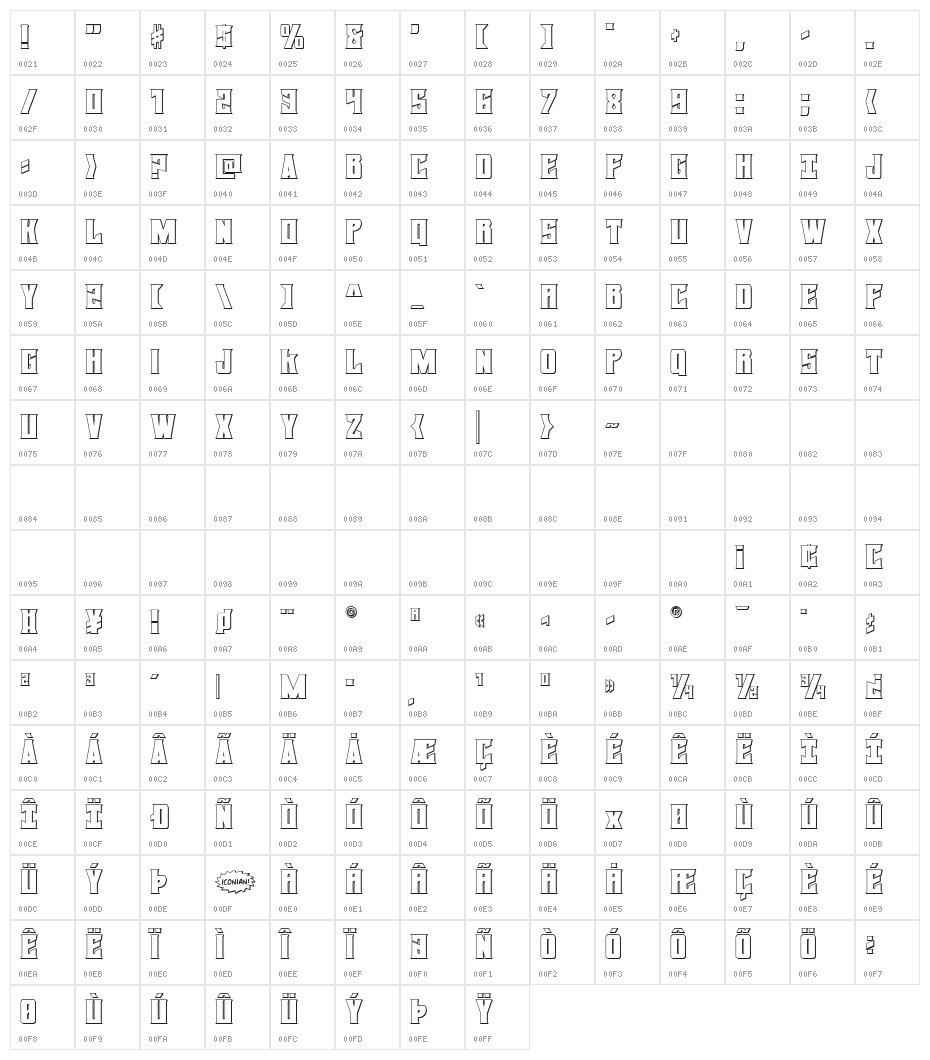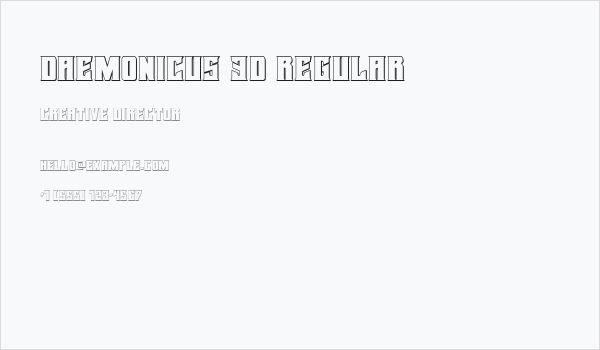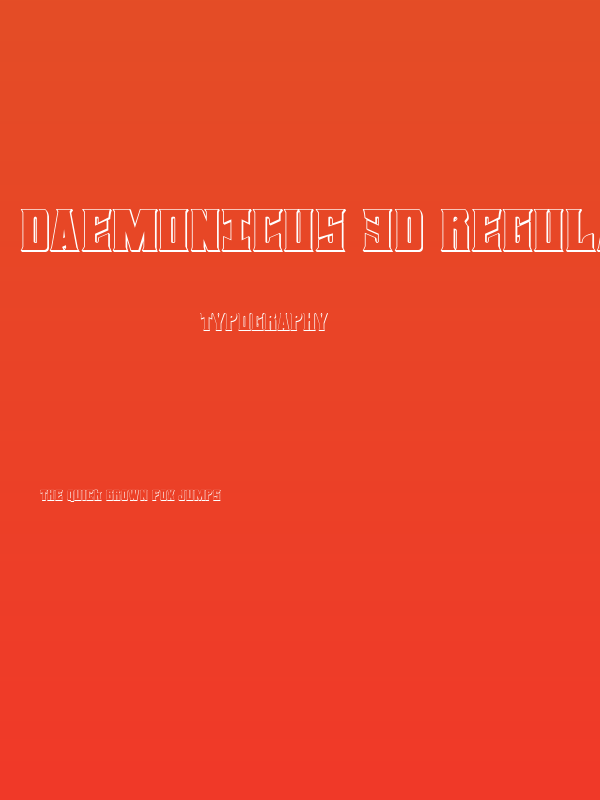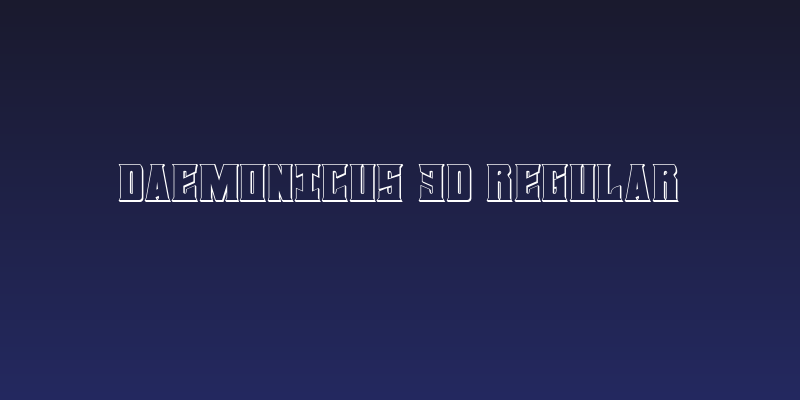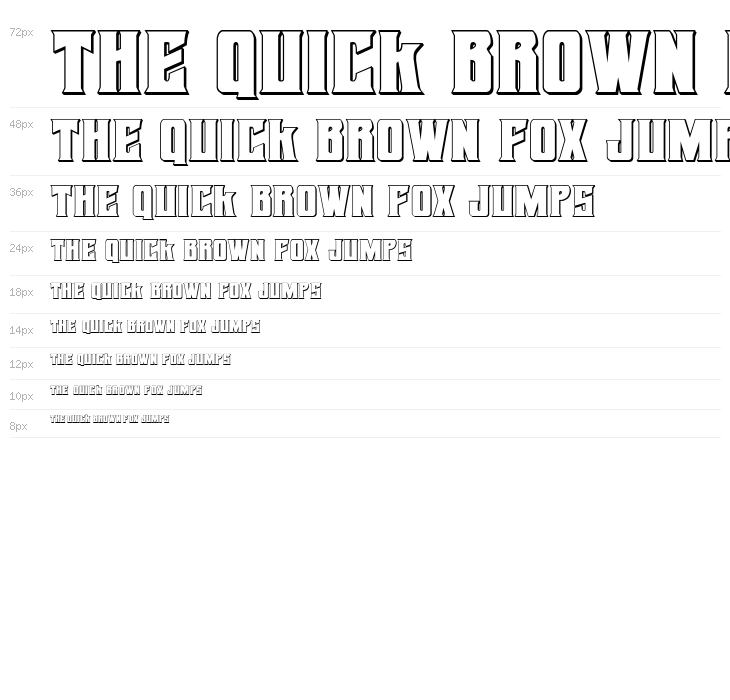
Daemonicus 3D Regular Font
| Vorgeschlagene Projekte | Ideal for video game titles, movie posters, sci-fi book covers, and branding that requires a modern, edgy look. |